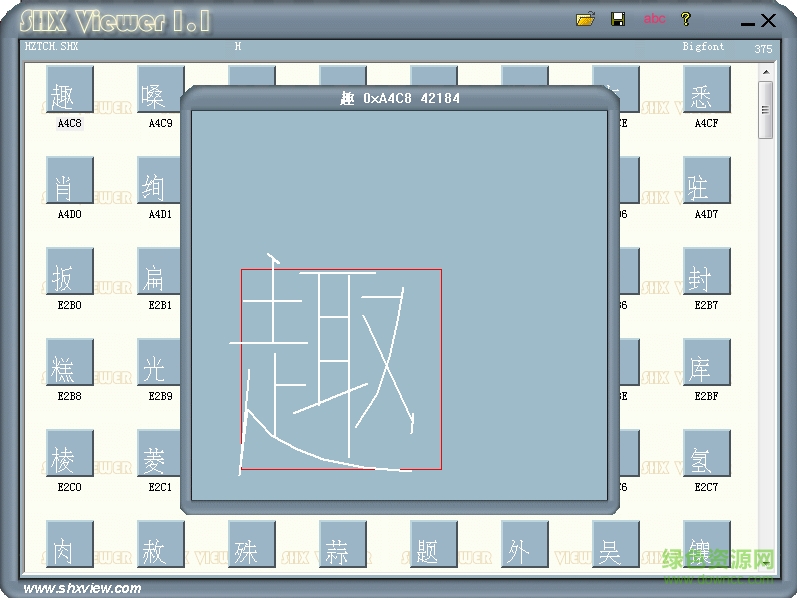
hztch.shx是一款擁有375個字符的cad大字體,有著簡潔清晰的行筆,字形大方嚴謹,讓你的平面設計、排版印刷更具美感,綠色資源網(wǎng)誠意推薦!
hztch.shx是一款cad字體,字體不是很完整,已有的字庫造型優(yōu)雅娟秀,有著印刷式的美感,如果您喜歡,來綠色資源網(wǎng)下載吧!
大字體是針對中文、韓文、日文等雙字節(jié)(全角)文字定制的字體文件。在文字樣式對話框中必須勾選“使用大字體”,才能在右側(cè)列表中選擇大字體文件。由于中文、日文的字符比較多,而且每個字符的定義都比較復雜,這類文件通常比較大,從幾百K到幾MB不等。